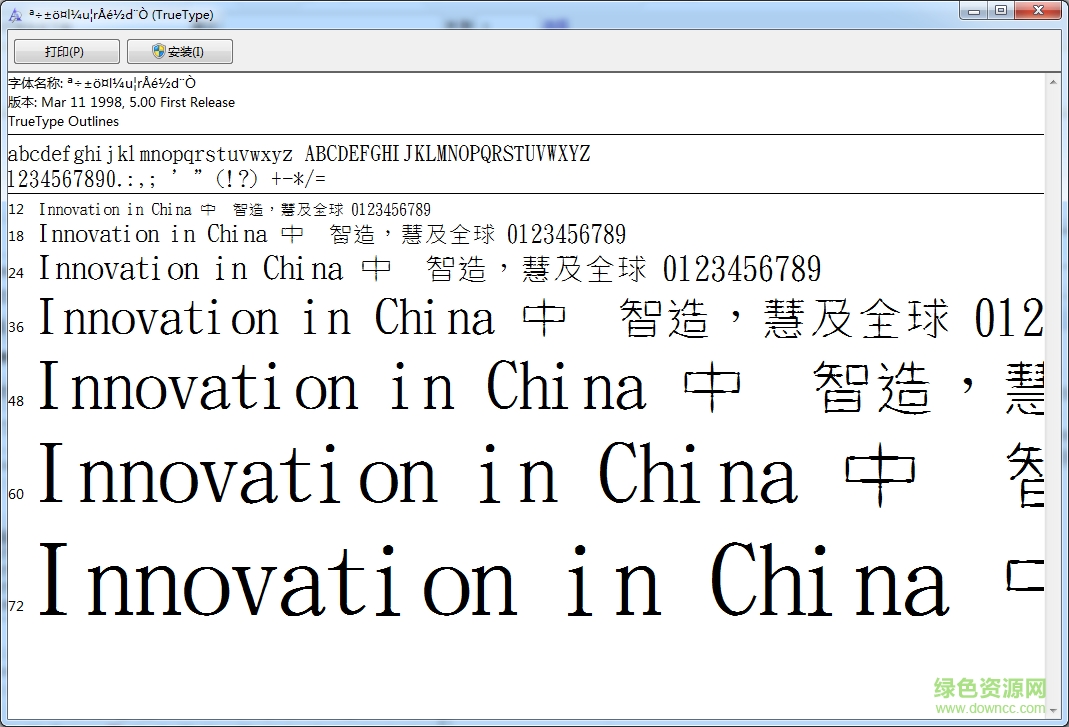
金梅子彈體是一款非常好看的金梅字體,字體筆畫(huà)有點(diǎn)斷斷續(xù)續(xù)的風(fēng)格,非常的別具一格,支持中英文和阿拉伯?dāng)?shù)字,非常適合廣告印刷行業(yè),喜愛(ài)的朋友趕快到綠色資源網(wǎng)下載體驗(yàn)吧!
用于美工設(shè)計(jì)方面的字體,該字體從整體上與普通字體并沒(méi)有什么差異,但仔細(xì)看可以發(fā)現(xiàn)該字體字形都是由一個(gè)個(gè)長(zhǎng)短不一的箭頭組成,看上去十分美觀,整體效果非常統(tǒng)一,且字庫(kù)完整,可以廣泛應(yīng)用于美工設(shè)計(jì)、海報(bào)、報(bào)紙雜志、影視制作以及內(nèi)容用字等領(lǐng)域,有需要的朋友可以免費(fèi)下載收藏